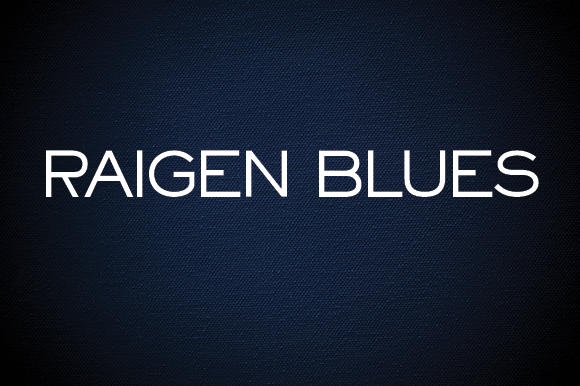
Creativefabrica Raigen Blues Font
[Creativefabrica] Raigen Blues Font
Raigen Blues - это минимальный и аккуратный шрифт без засечек.
Его можно легко подобрать к невероятно большому набору проектов, поэтому добавьте его в свои творческие идеи и обратите внимание на то, как он их выделяет!